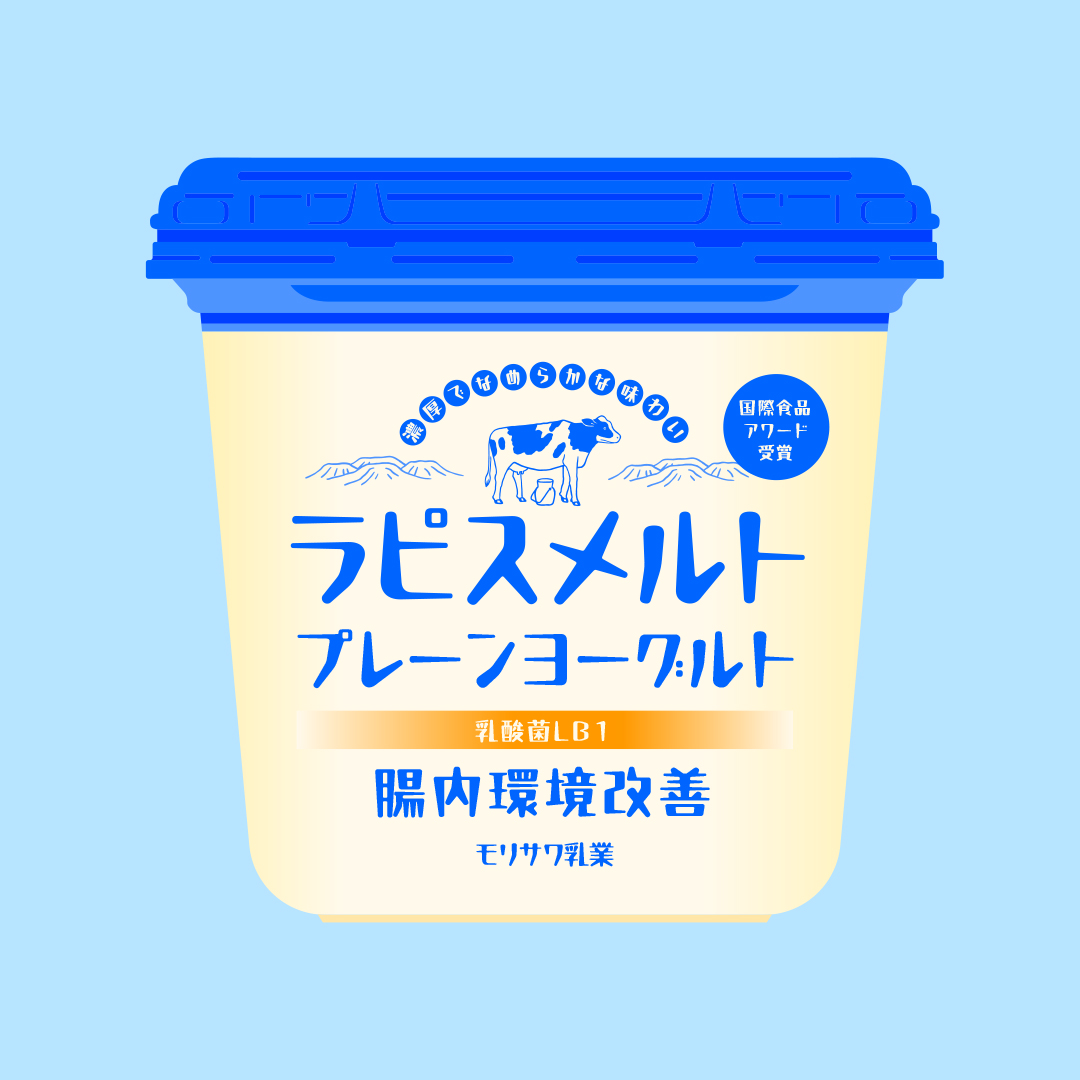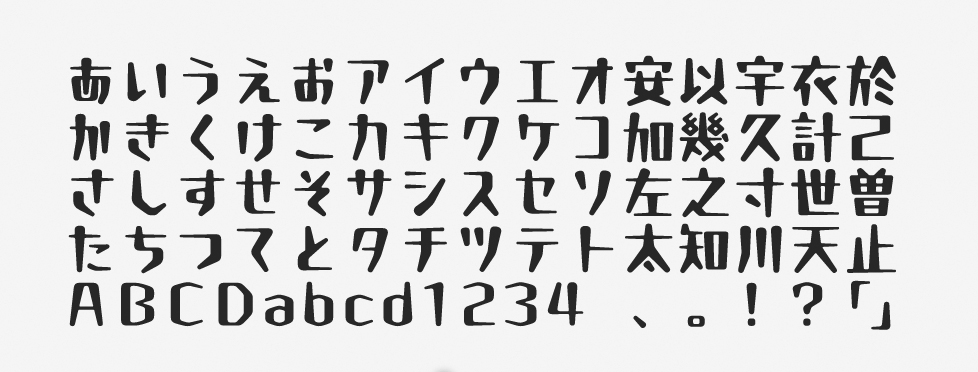
溶けるようなイメージを強調するには? 直線的でありながらもやわらかな「ラピスメルト」
~<主要なオススメ用途>ロゴ、商品パッケージ、ラベル、バナーなど~
【ラピスメルト 作例】ヨーグルトのパッケージ
「ラピスメルト」について
ラピスメルトは、2022年にリリースされたフォントです。直線のみで構成されたシンプルな設計のラピスエッジをもとに、丸ゴシック系のデザイン書体として開発されました。ラピスエッジのコンセプトを踏襲しつつ、角に丸みを持たせ、かな文字も自然な骨格へとアレンジされています。
「ラピスメルト」の特徴
ラピスメルトの線画の交差部分には、墨だまりのような処理が施されています。「メルト」の名前の通り、まるで文字が溶け始めているかのような雰囲気のフォントです。
それがやわらかなイメージにつながり、カーブのない幾何学的な骨格であることも相まって、電子的なコンテンツをやさしく伝える目的で特に活用されます。ウエイトごとに字幅が異なるのも特徴で、作例の「改」のつくりや「糸」など一部の文字では個性的な字形が採用されています。
作例はヨーグルトのパッケージのデザインであるため、滑らかさ、粘度、垂れている感じを表現するためにラピスメルトを採用しました。特に「溶ける」というイメージがキーポイントになるデザインでは、とても使いやすいフォントではないかと思います。
作例のポイント拡大
●書体名:「ラピスメルト」
●書体の分類:「デザイン書体」
●カテゴリ:「楽しい」「スタイリッシュ」「派手」
よく使われるシーン
タイトル・見出し、商品パッケージ、ロゴ、ラベル、POP、WEB、バナー、スマートデバイスの画面
「ラピスメルト」の書体情報
【ラピスメルト B】書体見本
Maniackers Design
デザイナー
Maniackers Design(マニアッカーズデザイン) 1995年設立。群馬県高崎市を拠点に活動しているデザインスタジオ。多様なクライアントワークと並行しながら、アートワークの制作や展示も頻繁に行っている。Webサイトでは1998年の開設以来、オリジナルフォントの配布も長年行っている。オリジナルキャラクター「おたふくま ぽくぽく」のプロジェクトも展開中。